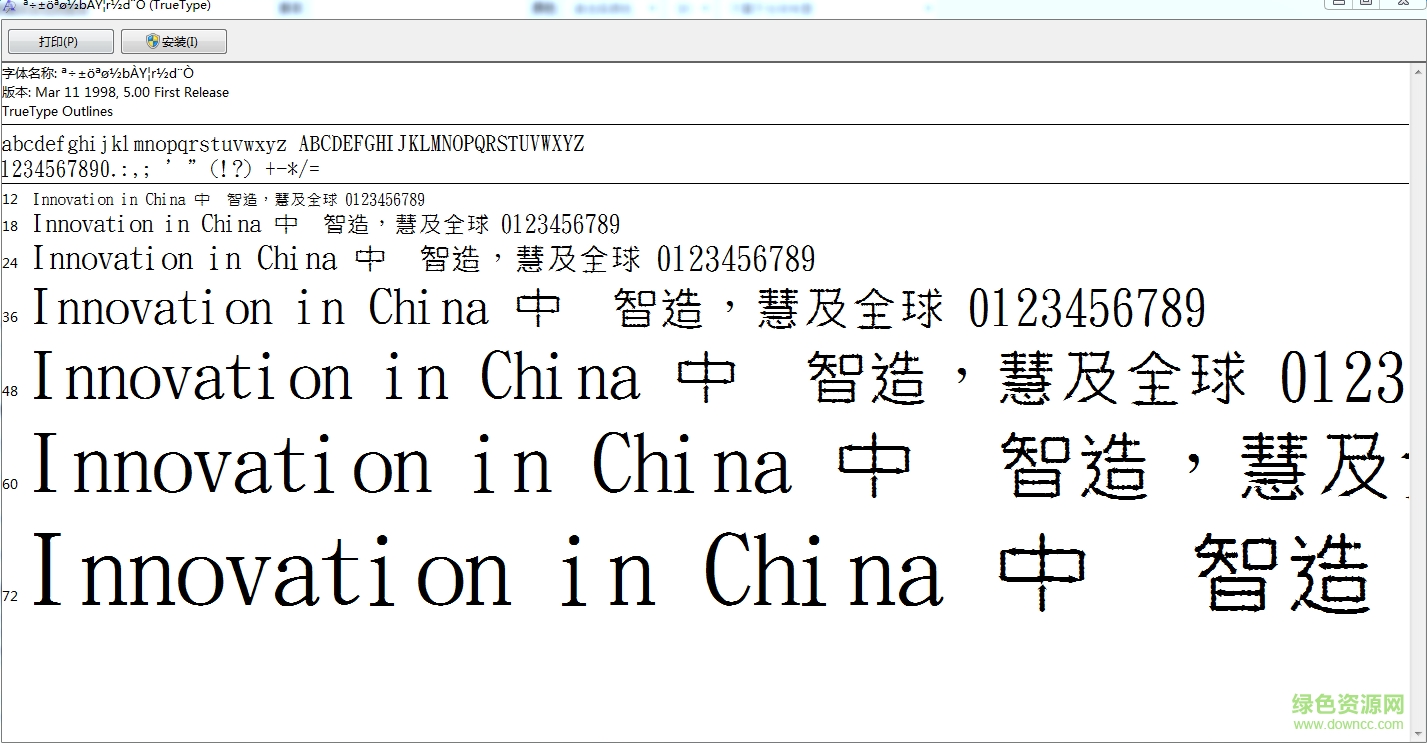
金梅長箭頭字繁體是一款工整的金梅字體,可以廣泛應(yīng)用于出版印刷、宣傳海報(bào)、美術(shù)設(shè)計(jì)等各個(gè)領(lǐng)域,讓你天都能擁有好心情設(shè)計(jì),有需要的朋友歡迎在綠色資源網(wǎng)免費(fèi)下載!
用于美工設(shè)計(jì)方面的字體,該字體從整體上與普通字體并沒有什么差異,但仔細(xì)看可以發(fā)現(xiàn)該字體字形都是由一個(gè)個(gè)長短不一的箭頭組成,看上去十分美觀,整體效果非常統(tǒng)一,且字庫完整,可以廣泛應(yīng)用于美工設(shè)計(jì)、海報(bào)、報(bào)紙雜志、影視制作以及內(nèi)容用字等領(lǐng)域,有需要的朋友可以免費(fèi)下載收藏